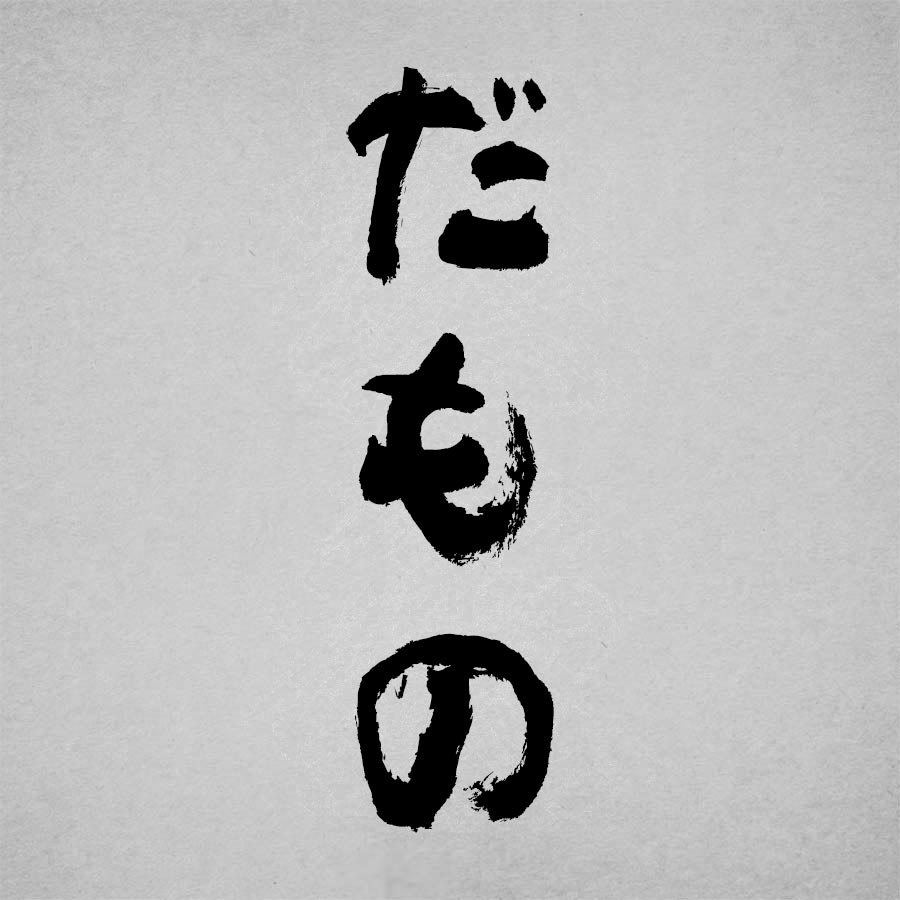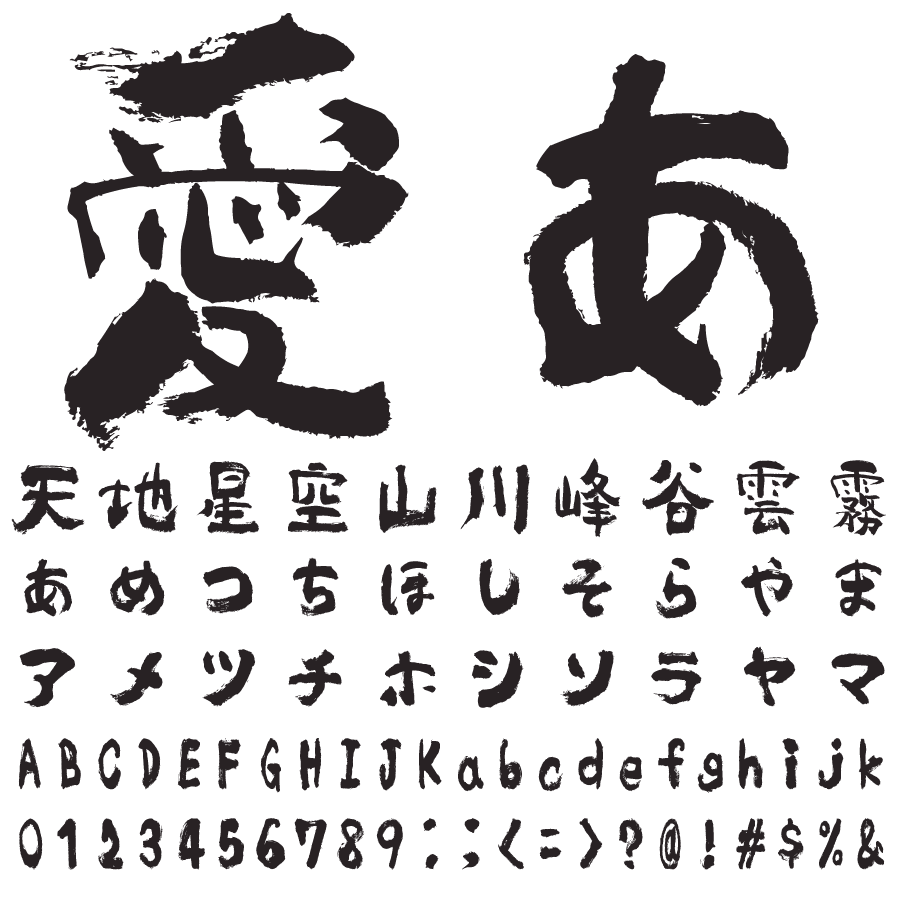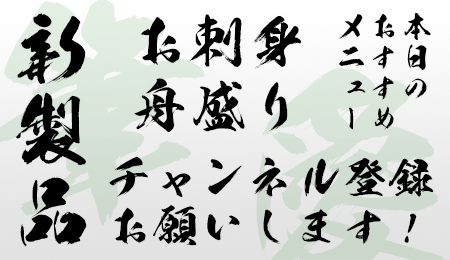
昭和書体
毛筆フォントの昭和書体:クオリティ高く楷書や行書、デザイン系まで
あらゆる使用目的にマッチする毛筆書体の提供を目指し、揮毫職人が1文字1文字丁寧に書き上げた本格毛筆書体ブランド『昭和書体』。看板、パッケージデザイン、テレビ、ゲーム、マンガやアニメなどプロの現場で使用されるナンバーワン本格毛筆書体ブランドです。
話題の人気アニメ「鬼滅の刃」「銀魂」でも採用された「闘龍」をはじめ最新作を含めたダウンロード版全ラインナップをご紹介いたします。
本格毛筆書体ブランド  昭和書体 とは?
昭和書体は、あらゆる使用目的にマッチする毛筆書体の提供を目指し、揮毫職人が1文字1文字丁寧に書き上げた本格毛筆書体ブランドです。
1950年頃から広告媒体製造業としての取組みを起源とし、2006年に毛筆フォント制作会社としてコーエーサインワークスを設立。2013年の組織変更を経て株式会社昭和書体に社名変更されました。直筆と見間違えるようなPC用毛筆書体制作にこだわりを持って、自社内ですべての制作業務を行い、和文毛筆という文化の継承に取り組んでいます。
返礼品の充実を目指す鹿児島県のさつま町が同社に声をかけ、2020年5月に特産品としては全国で初となるフォントの返礼品が誕生したことでも話題となりました。
昭和書体の特徴
書家「綱紀栄泉」が1文字1文字丁寧に書き上げた筆文字
昭和書体の多くの書体を手掛けてきた書家「綱紀栄泉 (つなのりえいせん)」。1人の書家が64種類もの形態の異なる毛筆書体を書き上げた例を他に見たことがありません。1つの書体には第一水準から第二水準までの約7,000文字が必要で、64書体に書き分けた文字は約50万字。書き直しを含めると2倍近くにものぼる気の遠くなる作業です。まさに奇人であり天才と言う他なく、現代の弘法大師と呼べる存在です。奇しくも紫雲山上宮寺 (しうんざんじょうぐうじ) という寺の長男として生まれている事も、何らかの仏縁を感じざるを得ません。昭和10年生まれの高齢ながら精力的に活動されていましたが、2022年3月惜しまれながらも他界されました。
現在は御子息の坂口茂樹氏が二代目栄泉としてその遺志を引き継ぎ、鋭意揮毫中です。
現代の弘法大師とも言える昭和書体の書家「綱紀栄泉」
書家「綱紀栄泉 (初代)」
昭和書体の使用例
おすすめの使いかた
居酒屋や飲食店のメニューや看板、SNS動画のテロップ・字幕など
華龍 作例1
居酒屋や飲食店の雰囲気を醸し出すフォントと、POPで遊び心を表現したい時におすすめなのが筆書体です。メニューや看板に使われることで、お店の雰囲気を魅力的に表現します。また、SNS動画に表示されるテロップや字幕にもぴったりで、視覚的な演出とともに遊び心を演出します。POPなデザインでお客様の目を引くなら、是非筆書体を活用してみてください。
タイトルやロゴ制作など
華龍 作例1
「タイトル・ロゴなど」を制作する際、目立つ場面での重要性は高まり、目を引きつけ、インパクトを与え、魅力を伝えることが期待されます。そのため、豪快で力強い書体を用いることで、視覚的な訴求力を高めることができます。例えば、タイトルやロゴにはスタイリッシュで洗練された書体、あるいは目立つ場面での視認性を高めるために大胆な書体を活用することもおすすめです。
スポーツ大会や競技会での横断幕や企業内で授与される賞状など
華龍 作例1
賞状や横断幕など、堅実かつ格式のあるシーンにはきっちりした場面に使いたい筆文字がおすすめです。賞状に使用される書体は、受賞者に厳粛な賞賛を表現するため、力強さや格式を備えています。その一方で、横断幕に使用される書体は、遠くから読み取りやすく、伝えたいメッセージを大胆にアピールできるような特徴を持っています。
感謝の気持ちを伝える手紙や商品・サービスの説明文など
華龍 作例1
手紙や商品の説明文など、感謝や詳細を伝える際に最適な書体を探しているなら、細身の筆フォントが役立ちます。文字の密度を適切に保ちつつ、文章を美しく整えられます。スマートで読みやすい印象を与え、コミュニケーションをより効果的にします。
高解像度書体、爽シリーズ、基本書体
昭和書体の書体ラインナップには高解像度書体と基本書体の2種類の書体デザインが存在します。このうち高解像度書体にはさらに、データサイズをより小さくした「爽」シリーズがあります。
高解像度書体、爽シリーズ、基本書体それぞれの文字をアウトライン化したときのアンカーポイントと、輪郭線の細部を比べたのが下の図です。
この図で分かるように、アンカーポイントが非常に多い高解像度書体は、かすれなど細部の再現性が高く、文字サイズを極端に大きくして用いる際、特に印刷用途でその威力を発揮します。
この高解像度書体の「かすれ」等を少なめに調整し、シンプルな輪郭にリメイクしたシリーズが「爽」シリーズです。従来の高解像度書体と比べ約3分の1のデータ容量になった「爽」シリーズは、シンプルな輪郭や軽量のデータが求められるカッティングや動画編集といった目的に筆文字を使用したいときに最適です。
最後に、基本書体シリーズは、主として目に優しい、柔らかく滑らかなデザインの毛筆書体がラインナップされているシリーズです。こちらも爽シリーズ同様にデータサイズが小さめですので、本文など大量の文字を使うシーンでの負荷が少なく、より快適に使用することが期待できます。
JIS90/JIS2004が選べる
ほとんどの昭和書体フォントでは、従来から広く利用されてきたJIS90規格のフォントの他、近年主流となりつつあるJIS2004規格のフォントもラインナップされています。日本語フォントを開発する複数のメーカーで採用されている慣例と同じく、昭和書体でも、JIS2004規格に準じたフォント名の末尾には"N"の文字を付与しています。
両規格では漢字のうち168字の例示字形が若干異なっており、概ねJIS90字形のほうが略字風、JIS2004字形のほうは正字・旧字風のデザインになっています。
JIS90/JIS2004で字形が異なる文字の例
JIS90字形
例: 闘龍爽
JIS2004字形
例: 闘龍爽N
NなしとN付きの字形差 (JIS90・JIS2004で例示字形が異なる文字の一覧)
JIS90規格とJIS2004規格で例示字形が異なる168文字のうち、シリーズ収録範囲に含まれる167文字を「闘龍」「闘龍N」で比較した一覧です。
(毛筆書体の特性上、明朝体やゴシック体ほどには字形差がはっきりしない文字もあります。)
書体一覧
高解像度書体 & 爽シリーズ
高解像度書体は、筆跡の輪郭を細部まで読み取ってデータ化することによりアンカーポイントを増やし、文字のかすれ等を最大限に再現。昭和書体を代表するシリーズです。
爽シリーズは、高解像度書体のカスレ等を極力少なくし、シンプルなラインにリメイクした書体。動画処理やカッティングシートなどの用途に向いているシリーズです。
豪龍書体豪龍爽書体
「豪龍」は、豪快な毛筆の力強さ及びかすれを最大に活かした高解像度毛筆書体です。シンプルラインでデータ容量を減らし、動画やカッティングシート用途に最適化した「豪龍爽」もあります。
雲龍書体雲龍爽書体
「雲龍」は、柔らかい曲線を活かしてかすれも残した高解像度毛筆書体です。シンプルラインでデータ容量を減らし、動画やカッティングシート用途に最適化した「雲龍爽」もあります。
白龍書体白龍爽書体
「白龍」は、和紙に書いた時の独特のにじみを最大に活かした高解像度毛筆書体です。シンプルラインでデータ容量を減らし、動画やカッティングシート用途に最適化した「白龍爽」もあります。
天龍書体天龍爽書体
「天龍」は、高解像度で仕上げたオリジナルの毛筆楷書体です。シンプルラインでデータ容量を減らし、動画やカッティングシート用途に最適化した「天龍爽」もあります。
黄龍書体黄龍爽書体
「黄龍」は、独特な筆の運びにより新しい毛筆の世界を成した高解像度毛筆書体です。シンプルラインでデータ容量を減らし、動画やカッティングシート用途に最適化した「黄龍爽」もあります。
黒龍書体黒龍爽書体
「黒龍」は、荒々しい龍の舞を表現した高解像度毛筆書体です。シンプルラインでデータ容量を減らし、動画やカッティングシート用途に最適化した「黒龍爽」もあります。
闘龍書体闘龍爽書体
高解像度毛筆書体「闘龍」。シンプルラインでデータ容量を減らし、動画やカッティングシート用途に最適化した「闘龍爽」もあります。
飛龍書体飛龍爽書体
高解像度毛筆書体「飛龍」。シンプルラインでデータ容量を減らし、動画やカッティングシート用途に最適化した「飛龍爽」もあります。
銀龍書体銀龍爽書体
「銀龍」は、龍が豪快にうねるような曲線を持った高解像度書体です。シンプルラインでデータ容量を減らし、動画やカッティングシート用途に最適化した「銀龍爽」もあります。